文字是语言的直接反映,是传载文化的最好媒介,是人际交往、商业来往的有效载体,当然也是社会经济发展的重要标志。因此,不管是大街小巷,还是城市街道,我们都能通过字来读懂信息,比如有活动宣传海报、有地铁公交广告、有墙体标语等等,每一个字体符号传递的是一种有效信息。但是怎么样才能提升消息传递的效果呢?字是亘古不变的,而唯一的也是最好的办法就是通过使用不同的字体,取得别样的效果,来实现不同的目的。下面,就为大家介绍一个优质的字体下载平台——字体视界。
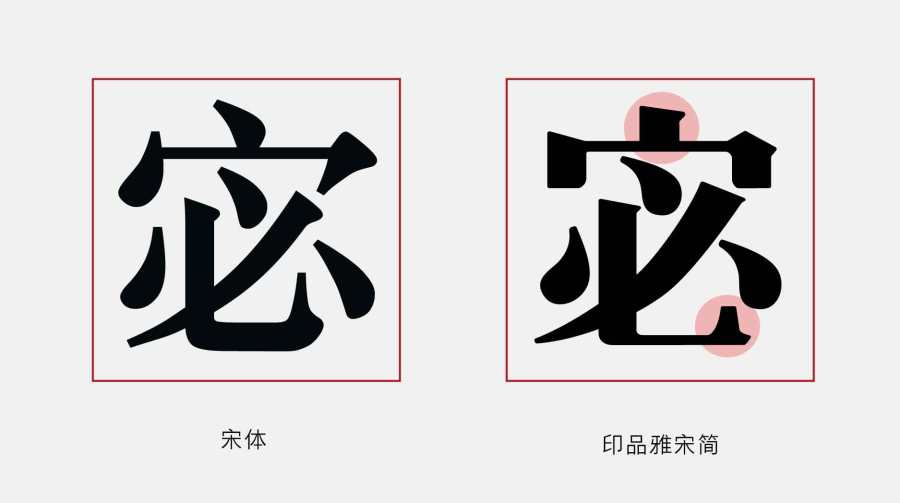
字体视界创新推出的各类字体,例如印品雅宋简字体,它比传统的宋体更富有个性、灵动活力,简洁大方,用户可根据需求自由选定字体,字体视界的字体都是原创正版,而且是拥有独立版权的,只要购买字体视界的字体授权,就可以放心的使用,无需担心后期使用过程中的版权问题。